지난 3년간 만들던 획기반 손글씨 폰트 에디터
일단 손글씨 쓰면 공간 분석해줍니다. 그리고 손글씨에서 폰트로 바꾸면서 두께와 획 스타일을 변경해서 폰트를 다양하게 찍어낼 수 있습니다. 획기반의 2가지 기술을 사용해서 영상자막용 애니메이션 폰트 작업이 순조롭게 마무리 되어 갑니다. 이제 불꽃으로 AI가 알아서 하겠죠 인간이 할 일은 대부분 한거 같습니다.
도형을 기준으로 가이드를 만들고 그걸 기반으로 폰트를 만듭니다.
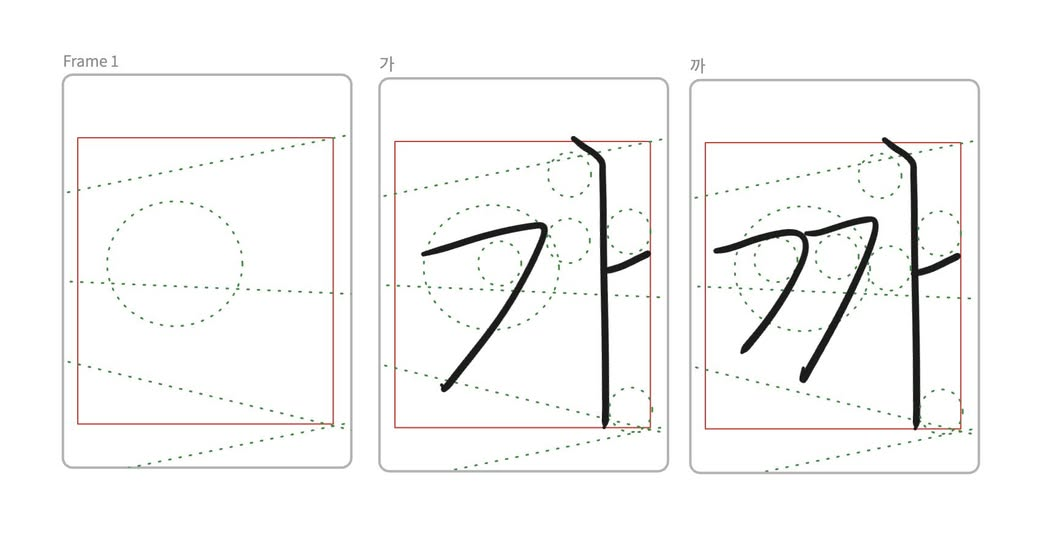
ㅏ 에 해당하는 글자는 사다리꼴을 사용합니다.
그리고 공간을 찾아서 조율합니다. 같은 원 사이즈에 공간이 비어야 조형적으로 아름다운 글자가 됩니다. 제가 만든 것은 획을 기반으로 하기 때문에 각도에 민감하고 3D로 회전하면 어떤 글자의 형태도 | 똑바른 글자의 형태를 만들 수 있습니다.
2D인데 변화값을 계속 유지하려는 이유는 동영상용 애니메이션 자막폰트나 시그니처 즉 사인을 그대로 영상으로 만들 수 있게 하려는 목적이 큽니다. 레이저커팅에도 사용할 목적이었지만 일단 다 나중에 하고
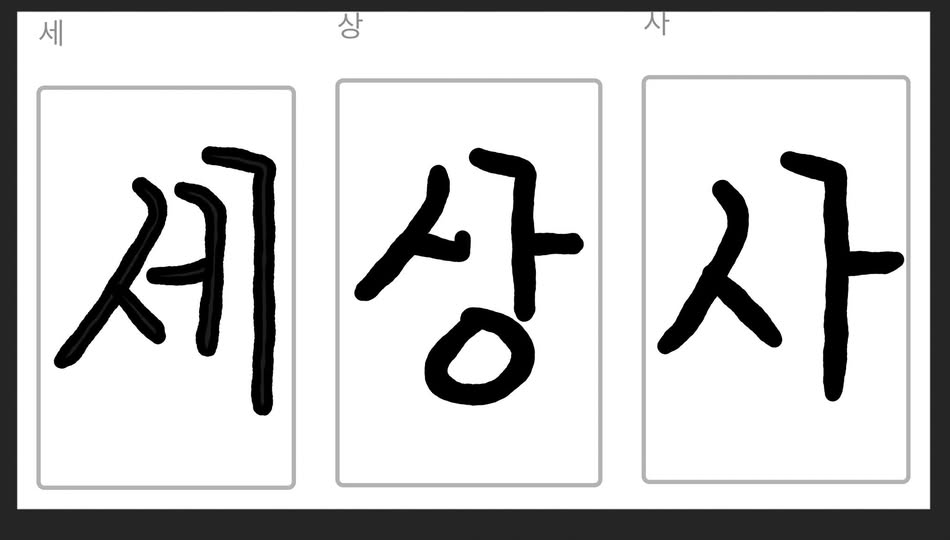
화면에서 쓰고 획을 기반으로 스트로크를 다른 형태로 변환시키면 옛글자, 판화스타일 등 꾸불꾸불한 느낌을 추가해서 획이 셰이프로 바뀌게 됩니다. 손글씨가 폰트로 마무리 되게 처리합니다.
자 이제 끝이 나고 만화폰트, 애니메이션 등등 마무리 합니다.